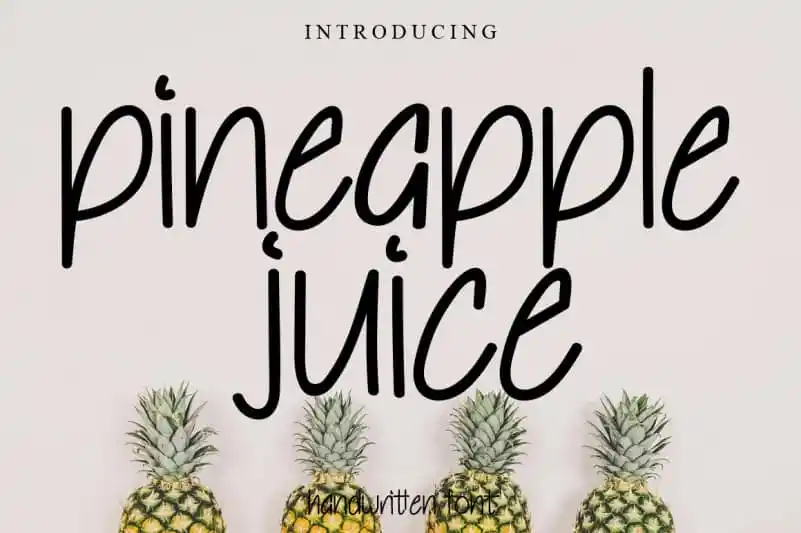
Pineapple Juice Handwritten Font – Download Grátis
A Pineapple Juice Handwritten Font é uma opção ideal para aqueles que procuram adicionar um toque relaxado e fresco a seus projetos de design. Suas linhas naturais e únicas são perfeitamente adaptadas à variedade de ideias criativas presentes no mercado, com o limite sendo somente o seu próprio imaginário. Este é mais do que uma fonte; ele é um instrumento de expressão que permite explorar diferentes estilos de escrita e personalizar qualquer design. Seja para adicionar um toque suave a um layout gráfico ou criar uma imagem única, essa fonte é certamente uma escolha inteligente. Com Pineapple Juice Handwritten Font, você pode dar vida à suas ideias de maneira autêntica e original, como se fosse uma tábua de marzipã na sua próxima criação visual.